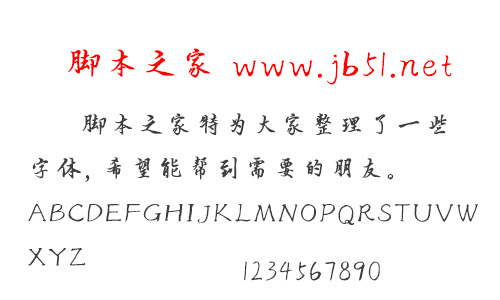
蘭米如煙輕舞字體是蘭米字庫推出的一款書法藝術(shù)字體,細(xì)雨如煙風(fēng)似劍,晨風(fēng)輕舞。字體筆觸較為粗實,字形端正,具有很好的視覺感,適合應(yīng)用于藝術(shù)設(shè)計、平面設(shè)計、網(wǎng)頁設(shè)計,書法字帖等領(lǐng)域,歡迎喜歡蘭米如煙輕舞字體的朋友前來下載使用。